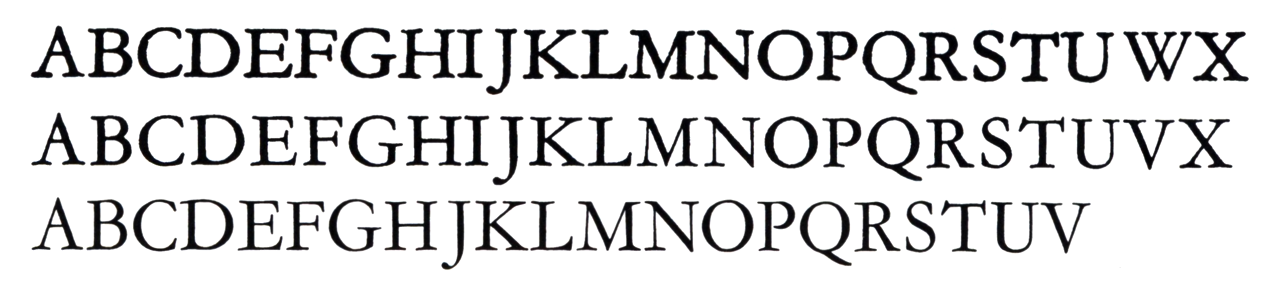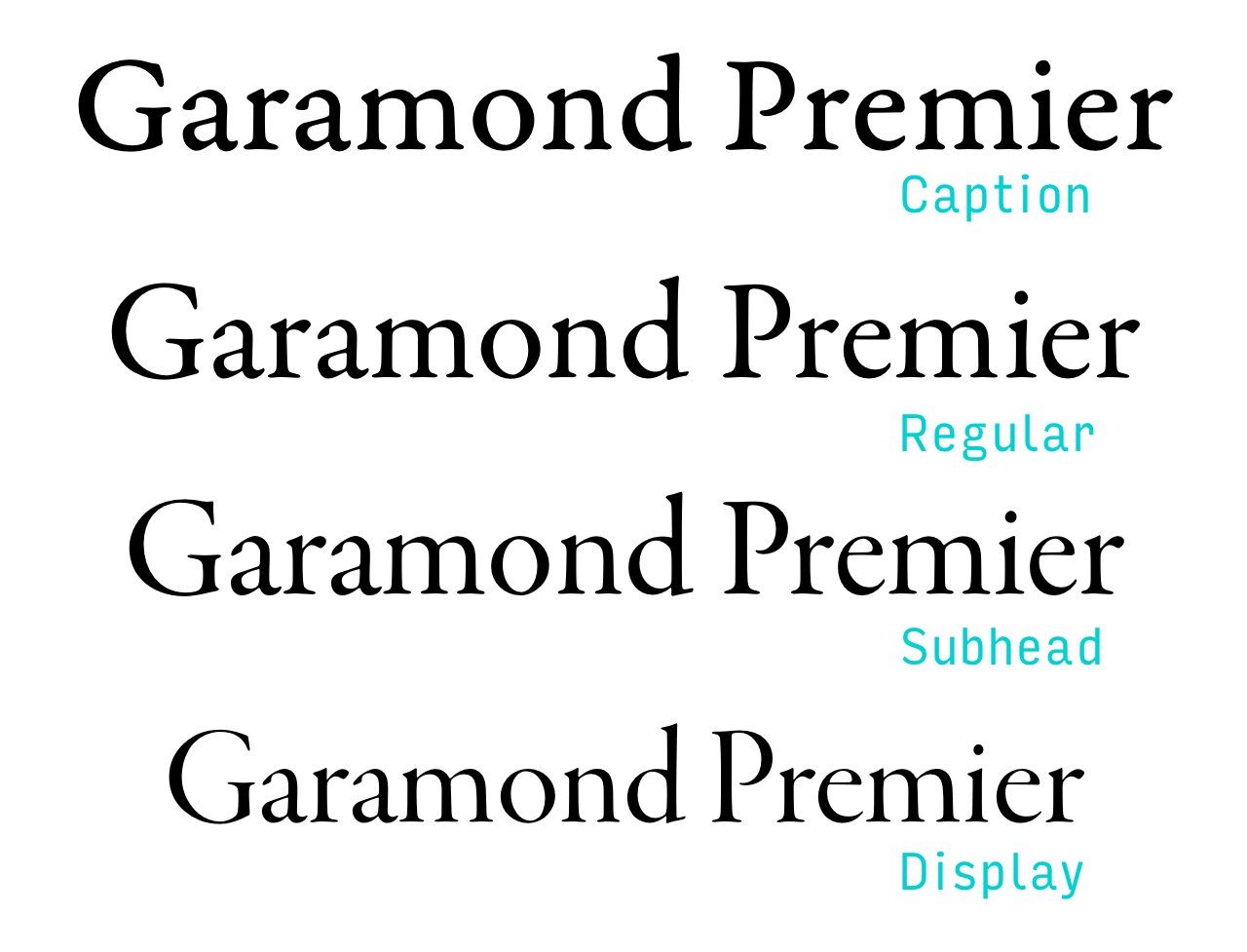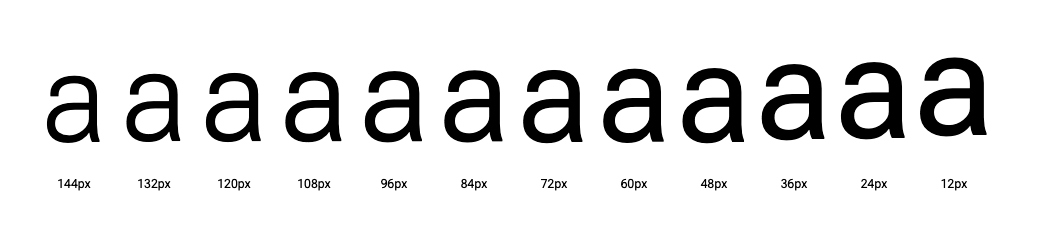
Odmiany optyczne
Każdy stopień czcionki jednego kroju jest inaczej zaprojektowany, ma inny rysunek znaków. Takie zróżnicowanie ma na celu zwiększenie czytelności tekstu w różnych wielkościach.
Różne stopnie czcionek (Monotype Garamond)
Czcionki 6 pt, 14 pt i 36 pt (Monotype Garamond)
Fonty przeważnie mają tylko jedną wersję, zoptymalizowaną pod konkretny stopień pisma, na przykład dla krojów dziełowych jest to około 10–12 punktów. Istnieją jednak kroje wydawane w kilku wersjach: odmianach optycznych.
Odmiany optyczne w foncie (Garamond Premier)
Technologia fontów wariacyjnych (ang. variable fonts) umożliwia zdefiniowanie osi wielkości optycznej (optsz). Jeśli projektant fontu odpowiednio oprogramuje zmiany wyglądu znaków, dobór można zastosować z dużą dokładnością.
Oś wielkości optycznej w fontach wariacyjnych (Roboto Flex)